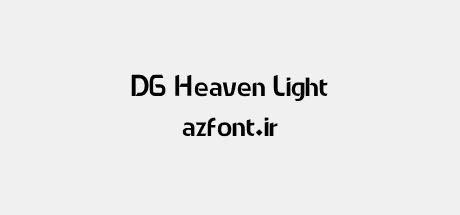
فونت زیبای رایگان DG Heaven Light
قلم زیبای DG Heaven Light از سری قلم های بسیار زیبا برای تایپوگرافی و لوگو تایپ می باشد.این قلم در وزن Regular و توسط https://twitter.com/HossamElNazawy طراحی و منتشر شده است.